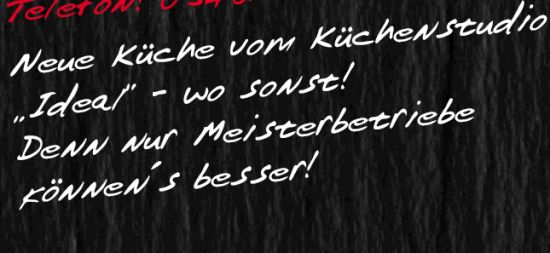
LennoxScript gesucht
kennt jemand dieses Font "LennoxScript"?
Ich habe es in einem PDF file gefunden als eingebettete Schriftart.
Wisst Ihr wo ich dieses font herbekommen könnte, denn ich finde
weder in google noch in anderen p2p Netzen etwas zu LennoxScript.
Nur ITC Lennox, aber da ist keine LennoxScript dabei.
Falls nicht, habt Ihr eine ähnliche Schriftart mit der man weiterarbeiten könnte?
Bei dieser Schrift scheinen mir die Buchstabenabstände sehr verbesserungswürdig zu sein. Bevor ich mir damit viel Arbeit mache, würde ich lieber, wenn irgend möglich, eine andere Schrift verwenden. (Aber was das gezeigt Beispiel angeht: Willst Du das nachbasteln, solltest Du auf jeden Fall einen Apostroph statt des Akzents verwenden.)
vielleicht ist dieser font ein privater selbstersteller, mit einem dieser "deine handschrift als font" programmen, anders kann ich es mir nicht erklären das diese schrift nirgendwo auftaucht.
ähnliche schriften gibts sicher wie sand am meer, da musst du dich einfach selbst mal durch myfonts wühlen.
Ihr habt Recht, es ist was freies oder selbstgemachtes oder exklusiv erstelltes ,doch das bezweifele ich.
Ich finde das Schriftbild halt schön zu lesen und auch dick genug, um es in einer Werbeaussage in Entfernung lesbar zu gestalten.
Glücklicher Weise habe ich herausgefunden, wer das erstellt hat. Werde den jatzt mal kontaktieren und versuchen das Geheimnis zu lüften.